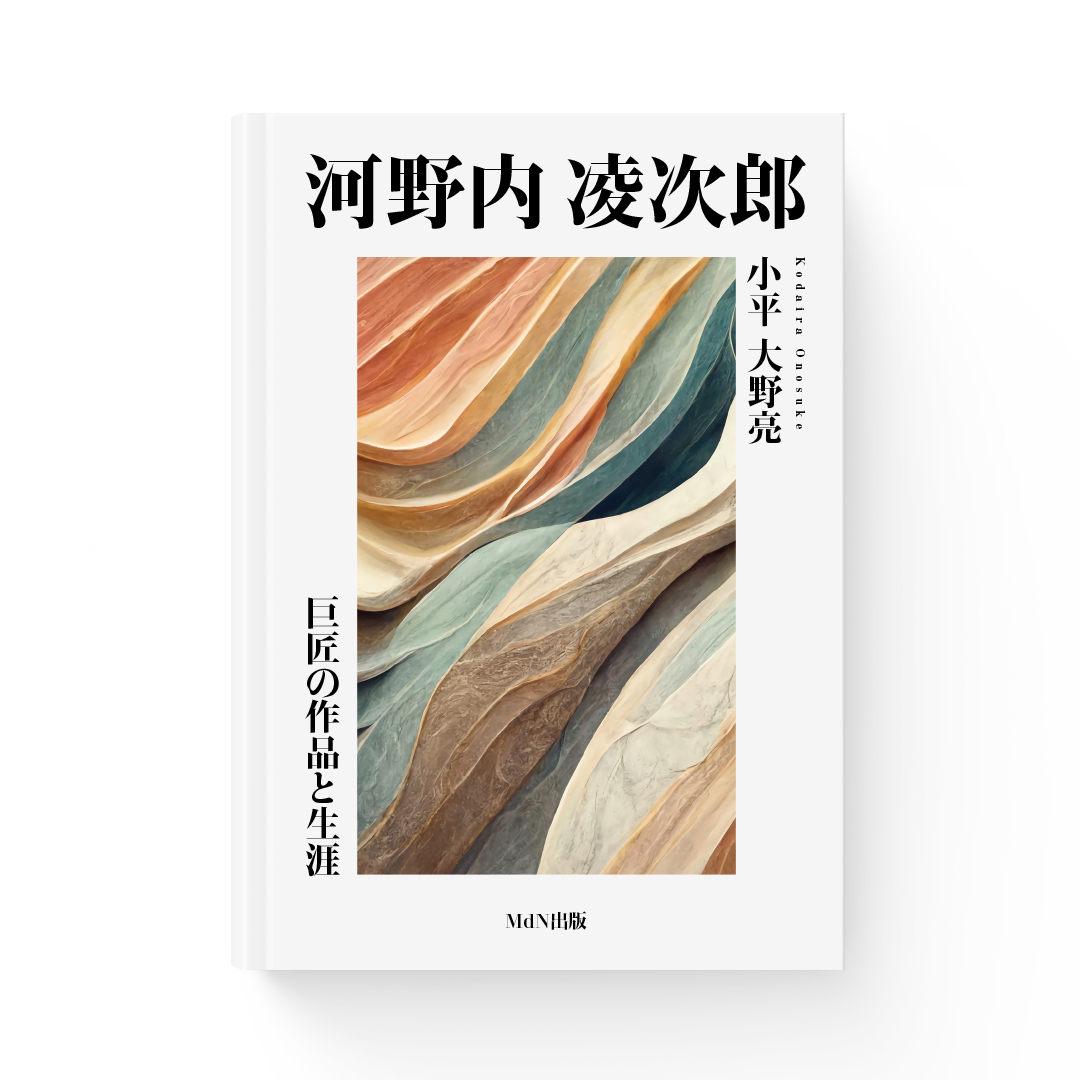
「光朝」について
光朝は、日本を代表するグラフィックデザイナー・田中一光氏(1930〜2002年)が書きためた文字をもとに、モリサワでデジタルフォント化されました。欧文書体のBodoniとの相性を考慮し、モダンな造形が追求されています。格式が高く、洗練されたシーンでの利用を想定して開発されたフォントです。
「光朝」の特徴
横画が極限まで細く、太くて力強い縦画の部分とのコントラストの高さが特徴的なフォントです。漢字の三角形のウロコもシャープで、洗練された印象が高められています。タイポグラフィ的な「文字で見せる」といった表現が可能なフォントで、堂々とした佇まいです。
光朝は見出しによく使われるフォントで、大きなサイズでの使用に適しています。格調の高さを感じさせたい媒体に効果的で、タイトルやポスターなどに使いやすいフォントになります。見出しで映えるフォントのひとつです。
作例は現代アートの巨匠の生涯を描いた書籍なので、品格・洗練といったイメージの表現ができる光朝を採用しました。作中に含まれる「河」や「涯」のさんずい、「凌」や「次」のにすいの力強さも特徴的なデザインです。
タイトル・見出し、書籍、パンフレット、ロゴ、ポスター